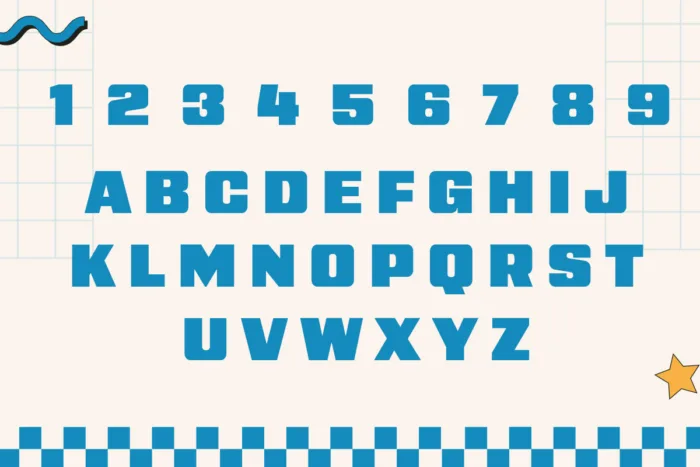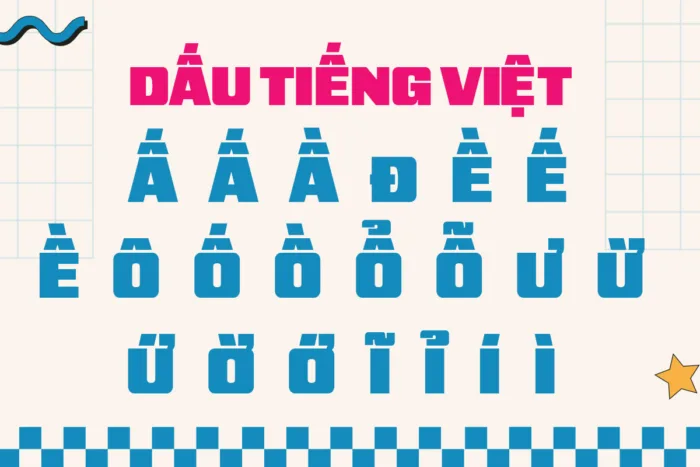
Retro Bold Việt hóa – Font chữ đậm và chắc chắn và vuông vức
Retro Bold Việt Hóa là một font chữ đậm chất hoài cổ, mang phong cách retro của những năm 70-80, nay đã được Việt hóa để hỗ trợ đầy đủ tiếng Việt. Với các ký tự dày dặn, góc cạnh nhưng vẫn có độ bo tròn mềm mại, font này tạo cảm giác mạnh mẽ, vui tươi và cực kỳ bắt mắt.
Phiên bản Việt hóa giữ nguyên tinh thần thiết kế ban đầu, đồng thời tối ưu các dấu tiếng Việt để đảm bảo tính thẩm mỹ và dễ đọc. Font phù hợp cho tiêu đề, poster, banner quảng cáo, thiết kế áo thun, logo hoặc các sản phẩm mang phong cách vintage và pop-art.
Bên cạnh đó, Retro Bold Việt Hóa kết hợp rất tốt với hiệu ứng bóng đổ hoặc gradient để tăng chiều sâu. Nếu bạn đang tìm kiếm một font chữ nổi bật, cá tính nhưng vẫn thân thiện với nội dung tiếng Việt, Retro Bold Việt Hóa chính là lựa chọn không thể bỏ qua!